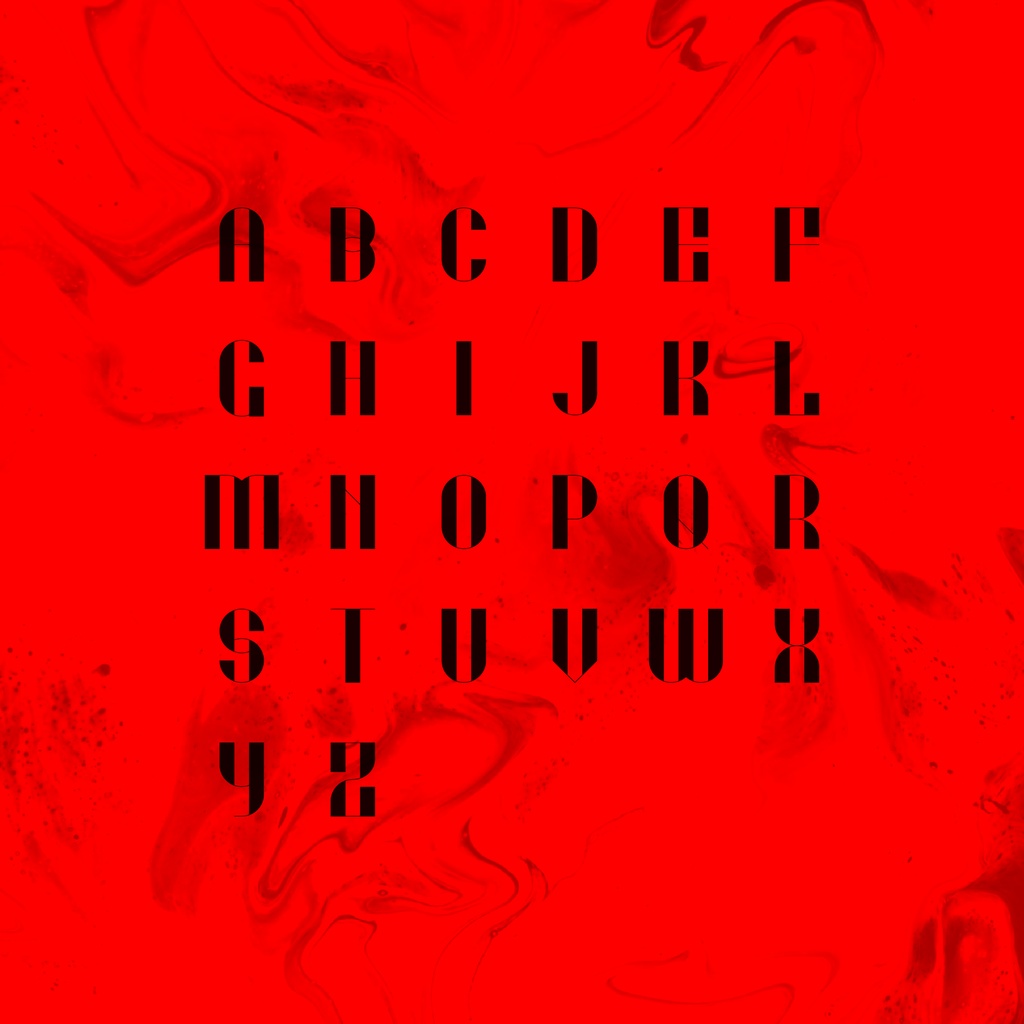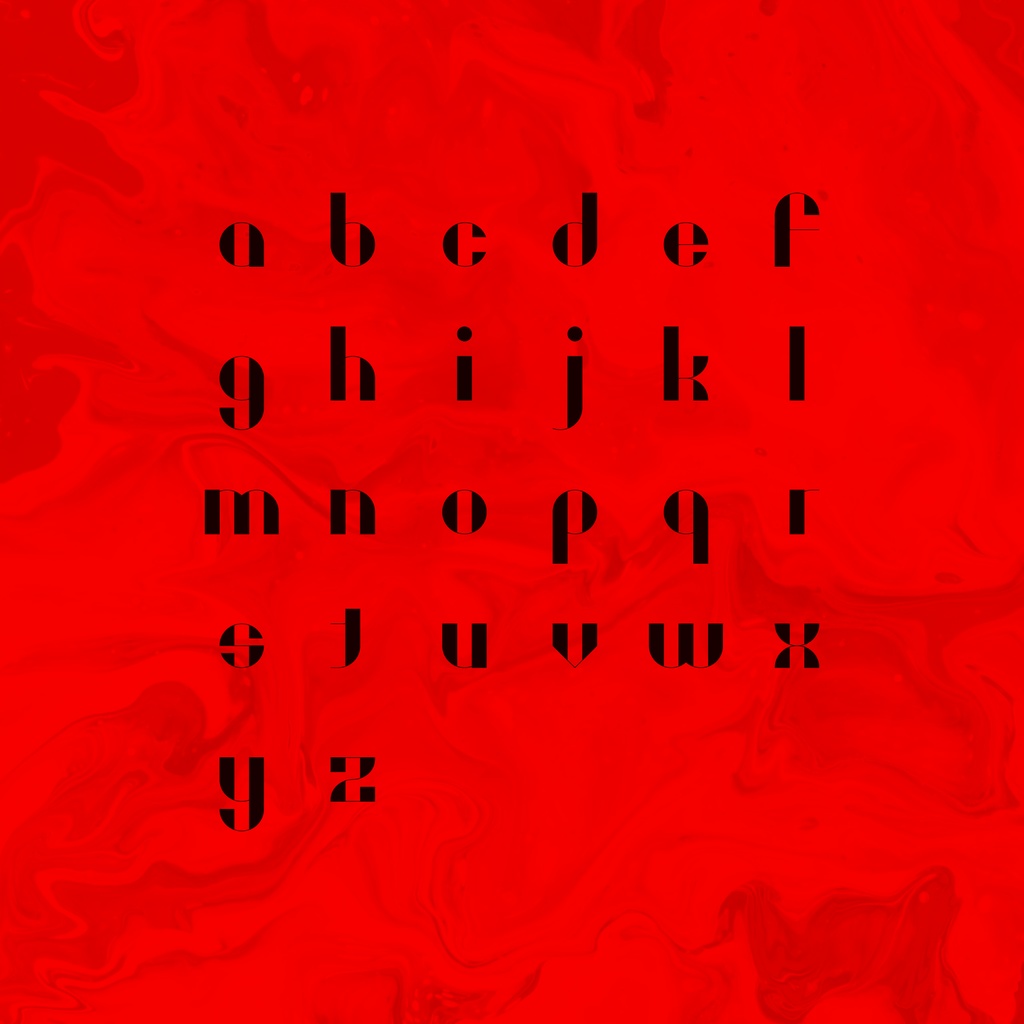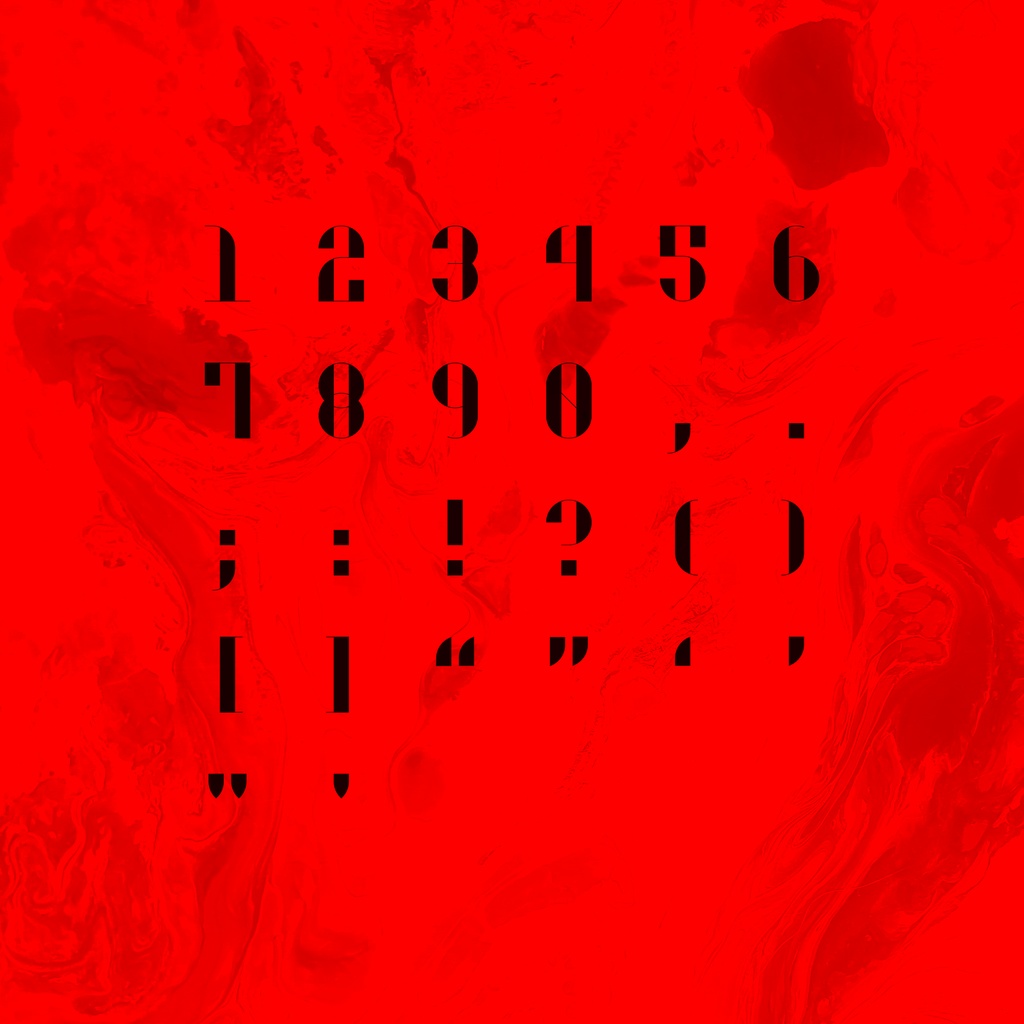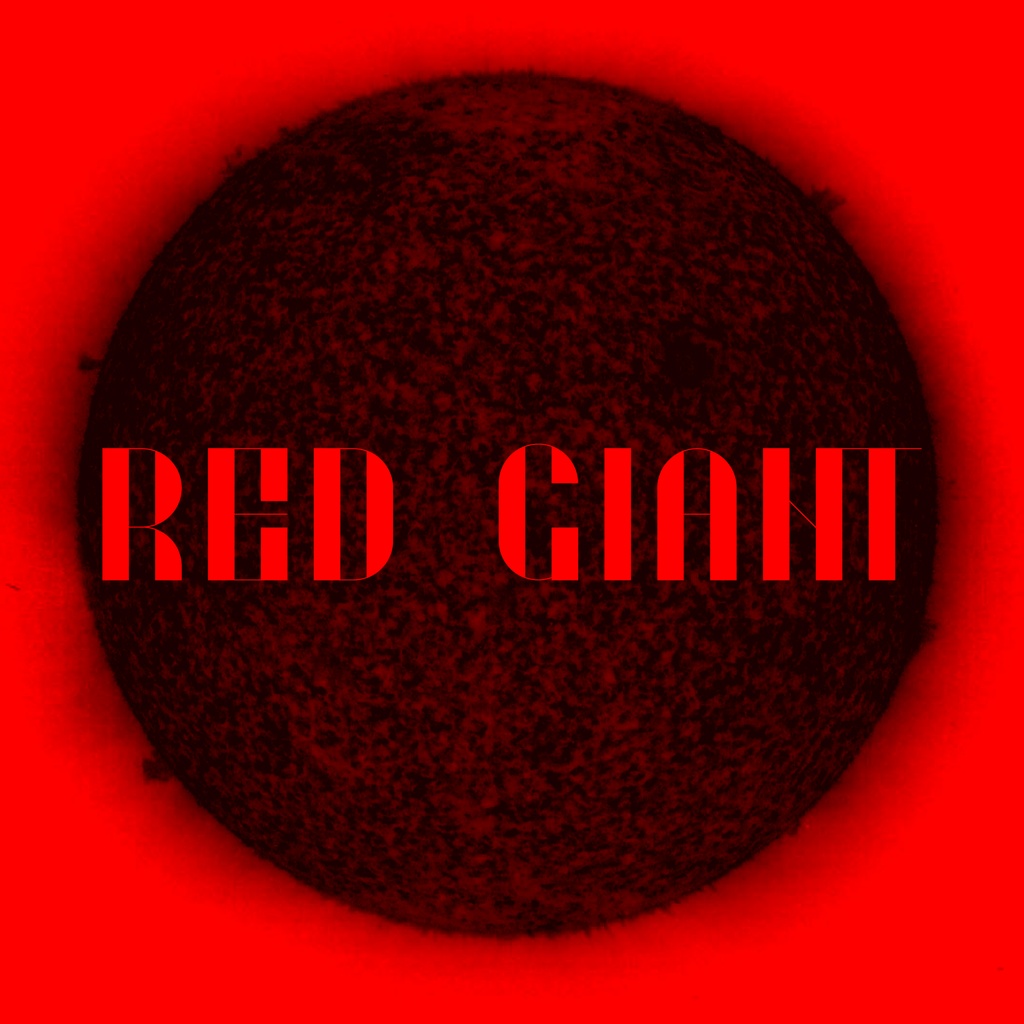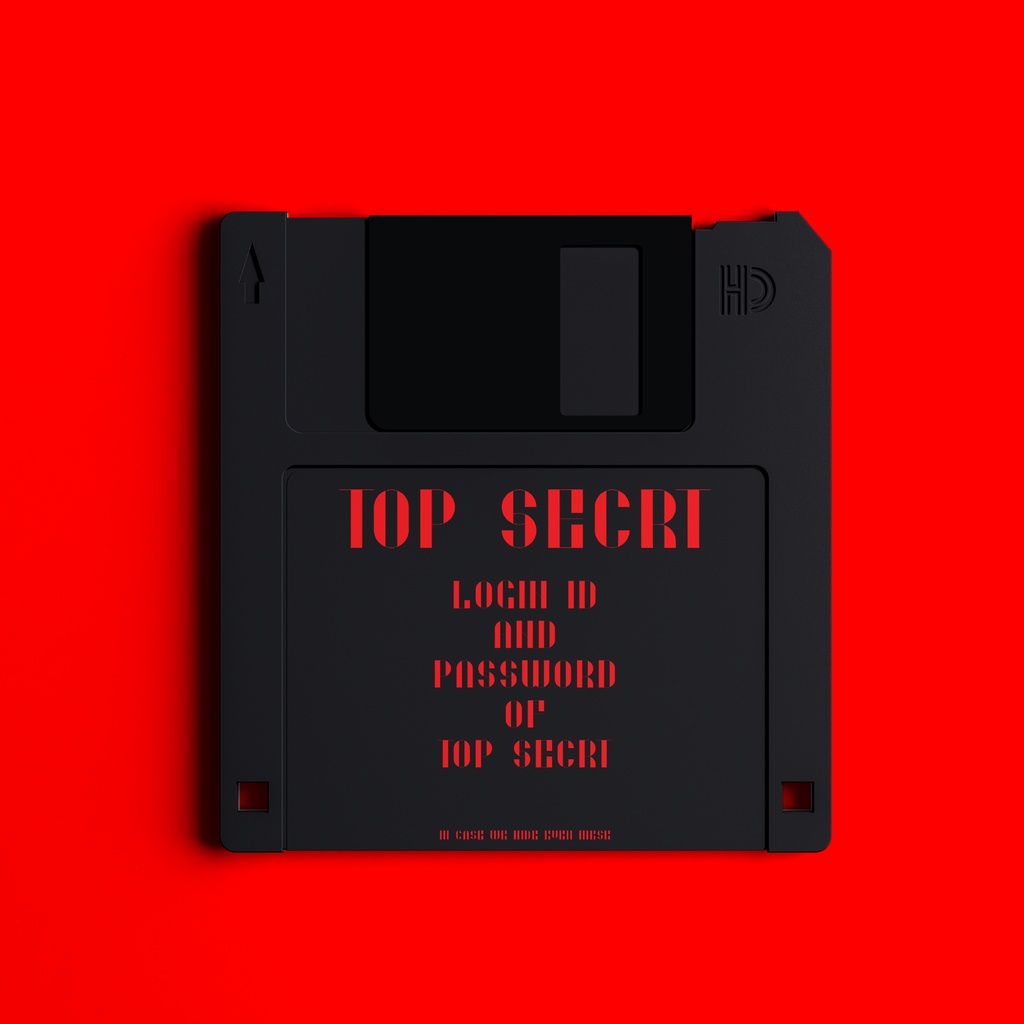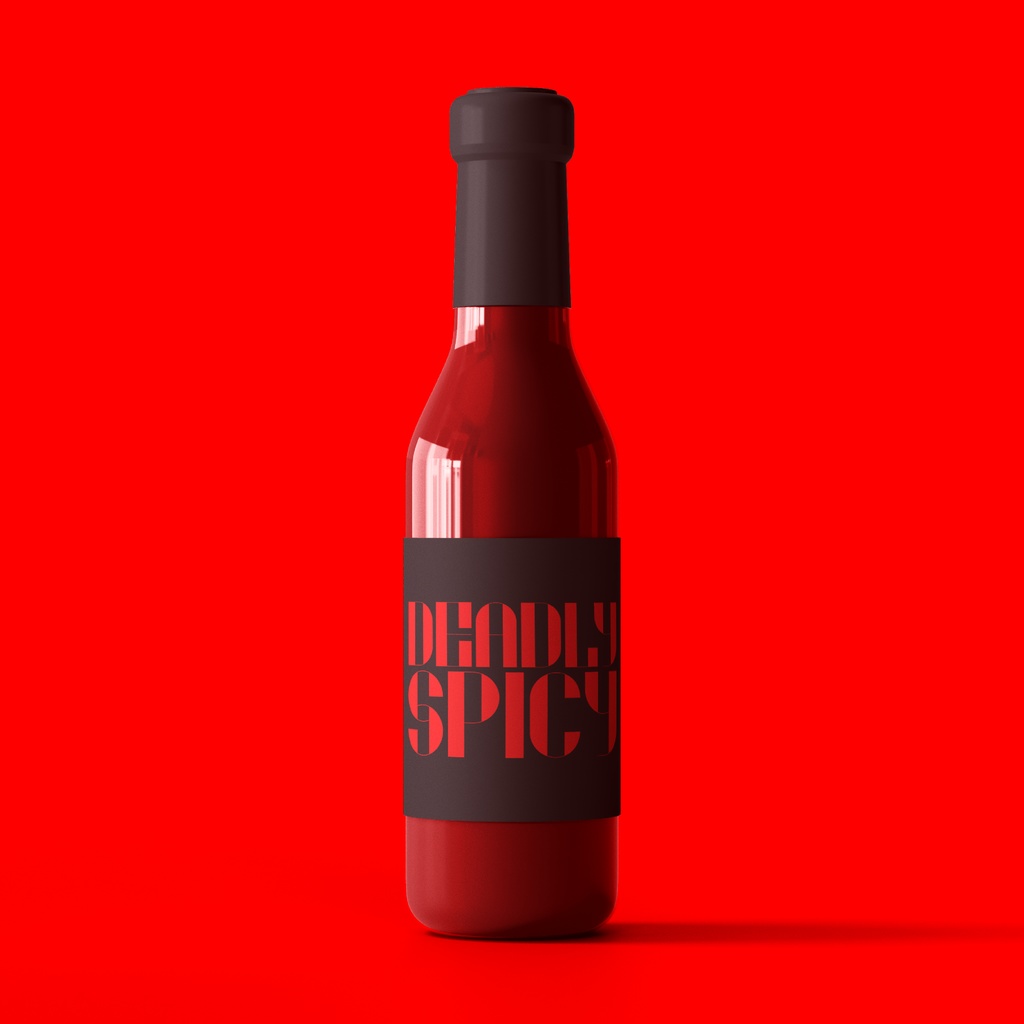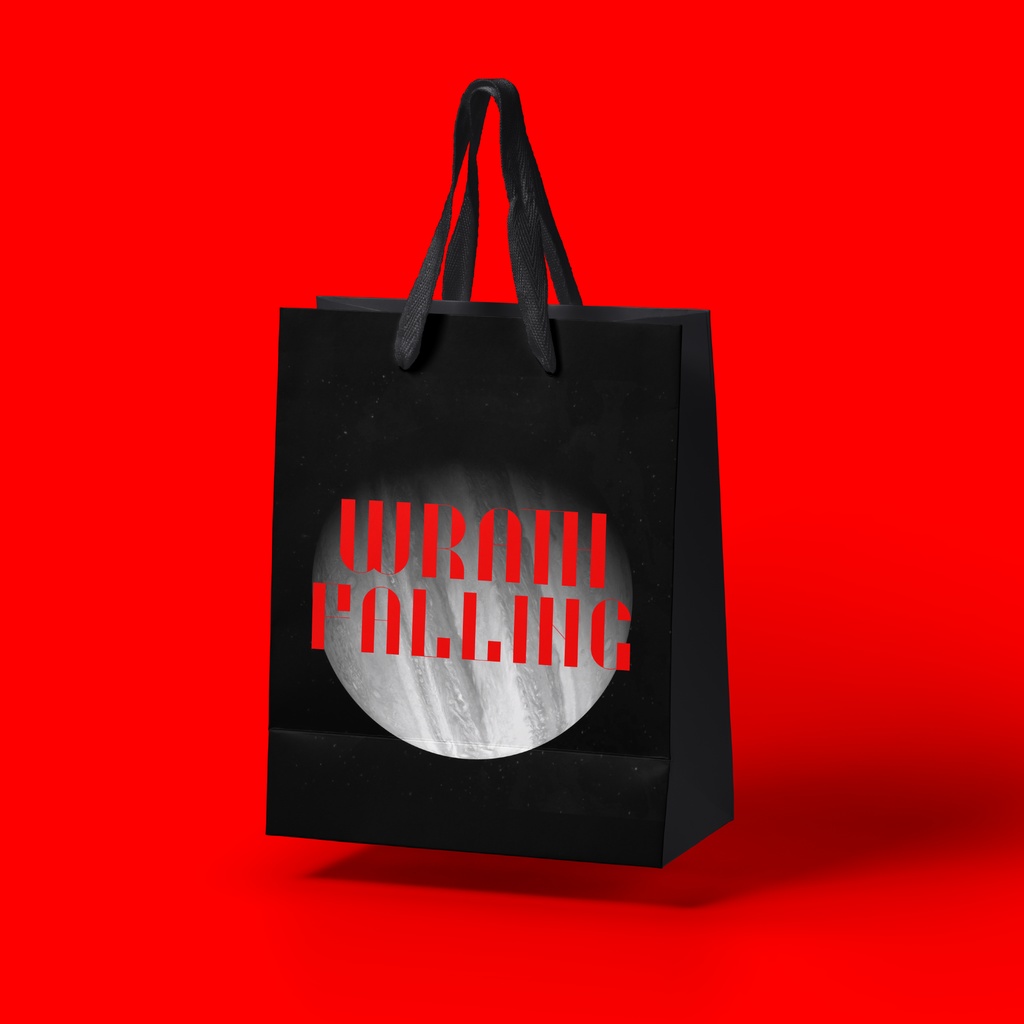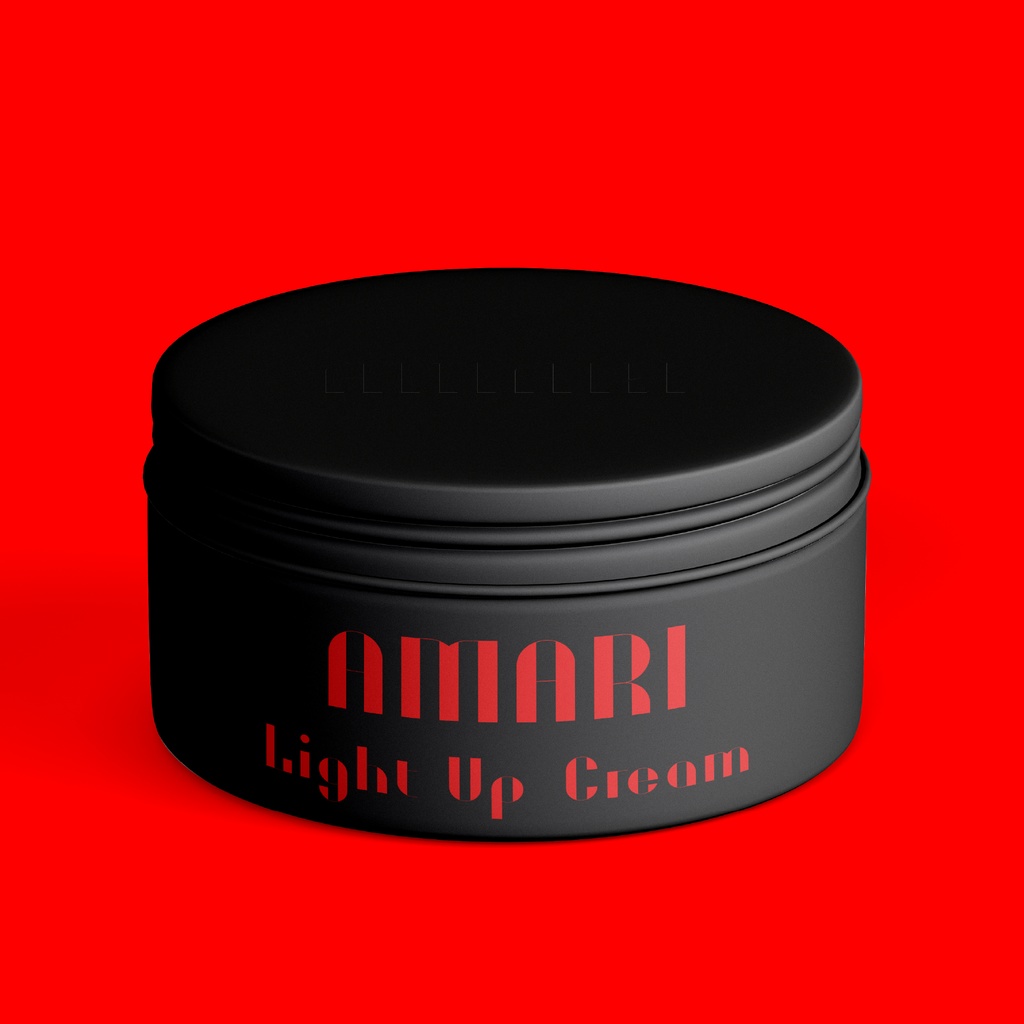
無料【フリーフォント】怒に堕ち Wrath Falling
怒に堕ち Wrath Falling「一時的に無料」 📢📢📢特記事項📢📢📢 英語だけのフォントです! このフォントは更新されない可能性があります。ご注意ください! 📢デザイン説明 怒に堕ちは去年の「Pancake」と「PIZZA ピザ」の作字を拡張した内容です。 縦書き部分のを強調、他の部分は弱めたの芸術的な装飾フォントです。 このフォントは、突然の思いつきから4日間で制作されました。 📢利用規約 このフォントは無料でダウンロードできる。 個人、商用どちらでも利用可能です。 もしもこのフォントが使用されたら、https://twitter.com/amari_designに教えていただけるとうれしいです! 本素材を使用した作品については、リツイートなどの形で宣伝させていただく場合があります。 フォントのインストール等の技術的なサポートはいたしません。使用して発生したと思われる如何なる問題についても、作者は責任を負わないものとします。 著作権を放棄することはありません。 商標を登録したり、作者であると主張したり、データ自体を販売または再販したりすることは禁じられています。 このコンテンツの最終的な解釈権は作者に帰属します。 内容補充とバージョン更新は製作続けるです。使用する際は最新バージョンにご注意ください。 📢収録內容 怒に堕ちはラテン文字、数字だけてを含む83文字が含まれています。 ーーーーーーーーーーーー Twitter:https://twitter.com/amari_design Behance:https://www.behance.net/9f45706b ーーーーーーーーーーーー